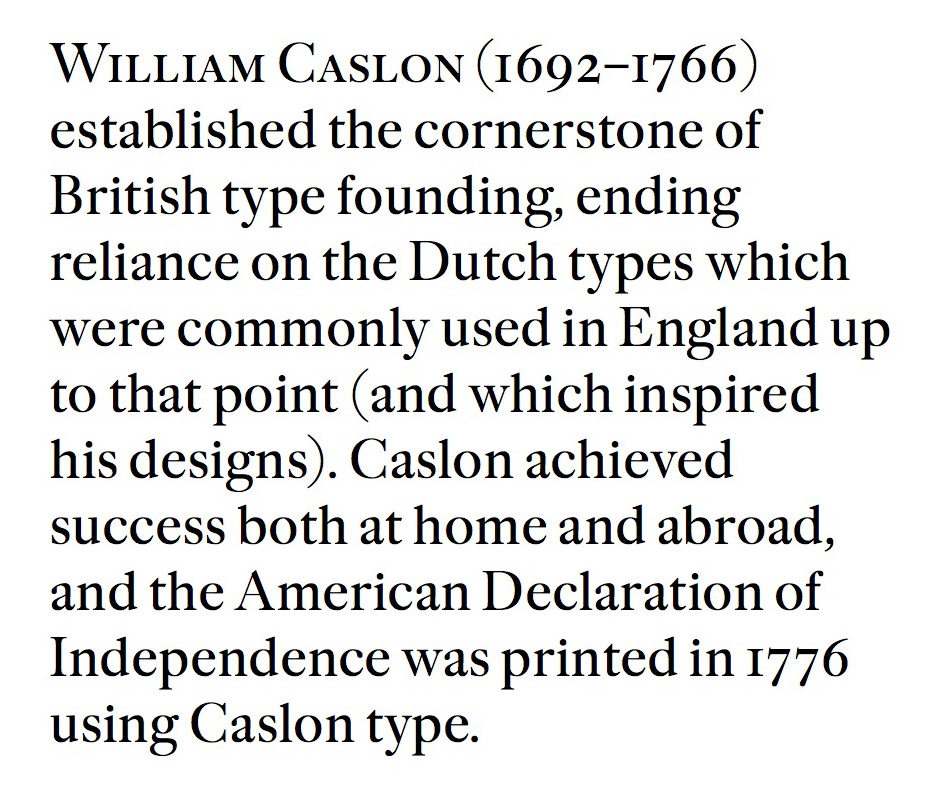
Пределы совершенства
Дав­но кру­тит­ся в го­ло­ве мысль за­пи­сать свои ощу­ще­ния от из­ме­не­ний фак­ту­ры, глад­ко­сти, иде­аль­но­сти кон­ту­ра в лет­те­рин­ге на кам­не, в кал­ли­гра­фии и шриф­те.
Эта мысль воз­ник­ла, ко­гда мы в Кем­бри­дже рас­смат­ри­ва­ли дос­ки, на­гра­ви­ро­ван­ные ма­стер­ской Кар­до­зо-Кин­дер­сли, иде­аль­ные с тех­ни­че­ской точ­ки зре­ния. По­ду­ма­лось, что ка­кие-то 20–30 лет на­зад они вы­гля­де­ли про­сто не­ве­ро­ят­но, не­уже­ли мож­но до­бить­ся та­ко­го со­вер­шен­ства, та­кой точ­но­сти ли­нии! А сей­час ма­ло кто осо­знаёт в пол­ной ме­ре, что это сде­ла­но вруч­ную (на­столь­ко гла­док и без­упре­чен ре­зуль­тат), и мы не мо­жем вос­хи­тить­ся ра­бо­той так, как вос­хи­ща­лись со­всем не­дав­но. До че­го не­ожи­дан­но, долж­но быть, для мно­гих по­вер­ну­лась ис­то­рия, и как из­ме­ни­лось вос­при­я­тие! Мог­ли бы пред­ска­зать са­ми ма­сте­ра, что вот так вдруг вме­сте с раз­ви­ти­ем тех­ни­ки глад­кость кон­ту­ра пе­ре­ста­нет вос­при­ни­мать­ся од­но­знач­но как иде­ал?
Па­мят­ная дос­ка фи­зи­ку Джо­се­фу Том­со­ну (1856–1940), об­на­ру­жив­ше­му элек­трон. Ма­стер­ская The Cardozo Kindersley Workshop, Кем­бридж. © Фо­то: Ве­ра Ев­стафье­ва, 2015
Глад­кость и бле­стя­щее со­вер­шен­ство кон­ту­ра руч­ной ра­бо­ты силь­но по­те­ря­ли свою цен­ность с по­яв­ле­ни­ем циф­ро­вых ин­стру­мен­тов (на­при­мер, в гра­ви­ро­ва­нии на кам­не). По­яви­лась воз­мож­ность (от­ча­сти ил­лю­зор­ная) для не­про­фес­си­о­на­ла до­би­вать­ся ре­зуль­та­та, ко­то­рый рань­ше тре­бо­вал боль­шо­го опы­та. В об­щем и це­лом за «ров­ность и глад­кость» те­перь от­ве­ча­ет ав­то­ма­ти­зи­ро­ван­ный ин­стру­мент. Че­ло­ве­че­ская ру­ка, на­о­бо­рот, ста­но­вит­ся но­си­те­лем не столь­ко ма­стер­ства и точ­но­сти, сколь­ко эмо­ци­о­наль­но­сти, спон­тан­но­сти — по край­ней ме­ре, в ожи­да­ни­ях зри­те­ля.
Си­сте­ма ко­ор­ди­нат пе­ре­вер­ну­лась. Те ве­щи, в ко­то­рых точ­ность руч­ной ра­бо­ты до­стиг­ла ка­ко­го-то сверхъ­есте­ствен­но­го ка­че­ства, вдруг ста­ли «про­ва­ли­вать­ся» в на­шем вос­при­я­тии и в на­шей оцен­ке. Ком­пью­тер де­ла­ет эту ра­бо­ту бы­стрее и де­ше­вле, при­смот­реть­ся мы не все­гда ус­пе­ва­ем, а при­кос­но­ве­ние ру­ки в иде­аль­ной руч­ной ра­бо­те по­чти не за­мет­но. На­учить ком­пью­тер де­лать так­ же, как это де­ла­ет жи­вой ма­стер, — ди­ко азарт­ная иг­ра... По­лу­ча­ет­ся, что со­вер­шен­ство­ва­ние но­во­го ин­стру­мен­та во мно­гом ин­те­рес­нее, чем ре­зуль­тат: вы­со­кое ка­че­ство уже до­стиг­ну­то, те­перь ин­те­рес­но де­лать то же са­мое, но дру­гим спо­со­бом (ско­рость и сто­и­мость остав­лю за рам­ка­ми).
Пре­дель­ной точ­но­сти в кал­ли­гра­фии до­би­вал­ся Гер­ман Цапф (1918–2015), ко­то­рый об­ла­дал уди­ви­тель­ным чув­ством иде­аль­ной фор­мы, не­ви­дан­ной рань­ше, и до­во­дил кал­ли­гра­фи­че­ские над­пи­си до со­вер­шен­ства, ре­ту­ши­руя кон­тур / Index Graphik
Глад­кость кон­ту­ра — как глад­кость до­ро­ги. По уха­бам не про­едешь, а по ров­ной и по­кры­той на­ле­дью до­ро­ге сколь­зишь и ле­тишь впе­ред. Сверх­глад­кий кон­тур бук­вы (да и дру­го­го объ­ек­та) за­даёт гла­зу вы­со­кую ско­рость (но не чте­ния, а ско­рее рас­смат­ри­ва­ния) — и взгляд не за­дер­жи­ва­ет­ся. Не­дав­но мы об­су­жда­ли с дру­зья­ми-кал­ли­гра­фа­ми, по­че­му ча­сто пре­крас­ней­шие кал­ли­гра­фи­че­ские ли­сты не чи­та­ют, хо­тя ав­тор при­да­ёт тек­сту боль­шое зна­че­ние. Воз­мож­но имен­но по той при­чи­не, что слиш­ком вир­ту­оз­ны и иде­аль­ны ли­нии, и взгляд про­бе­га­ет по ним без тру­да и очень бы­стро, на­сла­жда­ет­ся лёг­ко­стью дви­же­ния и ле­тит даль­ше.
Ра­бо­ты Рей­чел Ял­лоп — пре­дел иде­аль­но­сти кон­ту­ра, по ко­то­ро­му глаз сколь­зит и не мо­жет оста­но­вить­ся.
Рань­ше ше­ро­хо­ва­тость бу­ма­ги и рас­тис­ки­ва­ние крас­ки бы­ли не­из­беж­ны­ми, а те­перь в ка­ких-то слу­ча­ях мо­гут быть же­лан­ны­ми. Кон­струк­ти­вист­ские ри­сун­ки, чер­те­жи, шриф­ты на со­вре­мен­ной бу­ма­ге вы­гля­дят без­жиз­нен­но — в ори­ги­на­ле (мень­ше ве­ка на­зад!) они смяг­че­ны и оду­шев­ле­ны ося­за­емо­стью ма­те­ри­а­лов. Те же фор­мы, но в «иде­аль­ном» кон­ту­ре и без вы­ра­жен­ной фак­ту­ры бу­ма­ги те­ря­ют ком­му­ни­ка­тив­ность, взгляд про­ска­ки­ва­ет по ним.
Осо­бен­но сло­жен в «пе­ре­во­де» на со­вре­мен­ные ма­те­ри­а­лы «па­лоч­ный шрифт» — имен­но из-за то­го, что пре­дель­но прост и гео­мет­ри­чен. По­па­дая в мир, где гео­мет­рия ста­ла слиш­ком точ­ной (из­ви­ни­те за та­кой обо­рот), та­кой шрифт мо­жет стать не­ин­те­рес­ным и при­ми­тив­ным. В эпо­ху кон­струк­ти­виз­ма са­ма гео­мет­рия бы­ла ру­ко­твор­ной, ри­со­ван­ной, края гео­мет­ри­че­ских фи­гур ды­ша­ли ру­ко­твор­ной не­иде­аль­но­стью, по­это­му со­вре­мен­ные циф­ро­вые ин­тер­пре­та­ции кон­струк­ти­вист­ских шриф­тов из-за сво­ей чрез­мер­ной глад­ко­сти и точ­но­сти силь­но про­иг­ры­ва­ют тем ри­сун­кам букв, ко­то­рые пред­ло­жи­ли кон­струк­ти­ви­сты.
Мо­но­ши­рин­ный па­лоч­ный шрифт Б. Эм­ме из его кни­ги «Шрифт: Эле­мен­тар­ное ру­ко­вод­ство для прак­ти­че­ско­го ис­поль­зо­ва­ния в клу­бе, шко­ле, пи­о­нер-от­ря­де и т. д.» (Ле­нин­град, Гос. изд. изоб­ра­зи­тель­ных ис­кусств, 1931)
Ка­жет­ся, гля­нец и фак­тур­ность в гра­фи­че­ской куль­ту­ре в це­лом в каж­дый пе­ри­од со­хра­ня­ют при­мер­но оди­на­ко­вые про­пор­ции, про­сто пе­ре­ме­ща­ясь из од­ной сфе­ры в дру­гую, ме­ня­ясь ме­ста­ми — от кал­ли­гра­фии к на­бор­но­му шриф­ту, в ри­со­ван­ные над­пи­си и обрат­но. Если точ­ность и гля­нец вос­тор­же­ство­ва­ли в шриф­то­вом ди­зай­не — в кал­ли­гра­фии уси­лит­ся фак­тур­ность, и на­о­бо­рот, ко­гда кал­ли­гра­фия бы­ла точ­нее пе­чат­но­го кон­ту­ра, шрифт бо­рол­ся, но не про­би­вал­ся к точ­но­сти вос­про­из­ве­де­ния. Толь­ко пу­ан­со­нист, воз­мож­но, гре­зил иде­аль­ным кон­ту­ром, ко­то­рый на ли­сте ста­нет та­ким же иде­аль­ным, как и в пу­ан­со­не, ко­то­рый он вы­ре­за­ет.
Ка­кой про­стор для дис­кус­сий и вы­бо­ра даёт эта раз­ни­ца меж­ду ре­нес­санс­ным пу­ан­со­ном и от­тис­ком для ди­зай­не­ров, ко­то­рые вос­ста­нав­ли­ва­ют клас­си­че­ские шриф­ты: брать за об­ра­зец пу­ан­со­ны, или от­тиск, или что-то сред­нее? Ка­кая фор­ма бук­вы бы­ла же­лан­ной, ка­ким бы­ло на­ме­ре­ние пу­ан­со­ни­ста? Ка­кую по­прав­ку на не­ров­ность пе­ча­ти, гу­сто­ту крас­ки, ре­льеф­ность бу­ма­ги он за­кла­ды­вал в ди­зайн шриф­та? И что бы­ло слу­чай­но­стью или не­из­беж­но­стью?
Раз­во­рот из кни­ги Джейм­са Сат­то­на (James Sutton) и Ала­на Бар­тра­ма (Alan Bartram) An Atlas of Typeforms.
© Фо­то: Ве­ра Ев­стафье­ва / Percy Lund, Humphries & Co Ltd., London, 1968.
По­до­зре­ваю, что сим­во­лом точ­но­сти во­все не все­гда был на­бор­ный шрифт, так тес­но свя­зан­ный се­го­дня для нас с ме­ха­ни­зи­ро­ван­ным, ма­шин­ным ми­ром. Бы­ло и вре­мя, ко­гда, на­при­мер, не бы­ло ни­че­го точ­нее и тонь­ше офор­та, а кал­ли­гра­фия остро­ко­неч­ным пе­ром пре­вос­хо­ди­ла сво­ей без­упреч­но­стью все дру­гие тех­ни­ки со­зда­ния букв. Это уди­ви­тель­но, и мож­но пред­по­ла­гать, что про­цесс, ко­то­рый на ко­рот­ком рас­сто­я­нии вы­гля­дит как со­вер­шен­ство­ва­ние од­ной тех­ни­ки и до­ве­де­ние её до мак­си­маль­но­го ка­че­ства, при рас­смот­ре­нии из­да­ли ока­зы­ва­ет­ся все­го лишь од­ним из эпи­зо­дов не­пре­кра­ща­ю­ще­го­ся ко­ле­ба­ния и пе­ре­те­ка­ния свойств. До­стиг­нув край­ней фак­тур­но­сти, тех­ни­ка не ис­чер­па­ет се­бя, не вы­ро­дит­ся, а от­пря­нет и на­пра­вит­ся ис­кать дру­гие вы­ра­зи­тель­ные сред­ства, воз­мож­но, в точ­но­сти и лос­ке.
Мне ка­жет­ся, что в ка­те­го­рию «фак­ту­ры как приёма» не­ров­ность кон­ту­ра пе­ре­шла толь­ко в се­ре­ди­не ХХ ве­ка. И очень ве­ро­ят­но, что это на­ча­лось имен­но в то вре­мя, ко­гда ти­по­гра­фи­ка бы­ла на пи­ке «ме­ха­ни­зи­ро­ван­ной» эсте­ти­ки (мо­дер­низ­ма). Ма­сте­ра ве­ка­ми бо­ро­лись за точ­ность вос­про­из­ве­де­ния шриф­та, и се­го­дня у нас и век­тор то­чен, и бу­ма­га пре­крас­на, и крас­ка мел­ко­дис­перс­ная — всё хо­ро­шо! Од­на­ко нам вновь за­хо­те­лось не­со­вер­шен­ства, и фак­ту­ра, не­ров­ность — те­перь ис­клю­чи­тель­но ху­до­же­ствен­ный приём, а не не­пре­одо­ли­мый фак­тор.
На­ме­рен­ная и управ­ля­е­мая ше­ро­хо­ва­тость как приём. Со­ло­мон Те­лин­га­тер. Но­во­год­нее по­здрав­ле­ние, 1960-е. Ори­ги­нал / Рос­сий­ская го­су­дар­ствен­ная биб­лио­те­ка.
При од­ном и том же «те­ле» фор­мы кон­тур мо­жет быть как глад­ким, так и «по­трёпан­ным», что ме­ня­ет и до­пол­ня­ет об­раз. Рва­ный край над­пи­си даёт гла­зу воз­мож­ность доль­ше бро­дить по ней и рас­смат­ри­вать, рас­по­ла­га­ет к бо­лее близ­ко­му кон­так­ту. Ин­те­рес­но, шрифт и кал­ли­гра­фия — па­ра ли это, ме­ня­ю­ща­я­ся ме­ста­ми в сво­ей экс­прес­сии и, на­о­бо­рот, в иде­аль­ной точ­но­сти? Два про­ти­во­по­лож­ных свой­ства кон­ту­ра, оди­на­ко­во не­об­хо­ди­мые для гла­за, при из­ме­не­нии од­ной тех­ни­ки стре­мят­ся про­явить­ся в дру­гой тех­ни­ке и сфе­ре.
Юрий Гор­дон. Га­зе­та Alcools. Вы­пуск № 7, 2006. Для оформ­ле­ния «Ал­ко­го­лей» ди­зай­нер раз­ра­бо­тал шриф­то­вую се­мью Ко­стро — ан­ти­кву и гро­теск. Обе гар­ни­ту­ры бы­ли на­ри­со­ва­ны в «Пей­н­те­ре» са­мой при­ми­тив­ной ки­стью, «как если бы на­ре­за­ны вруч­ную для вы­со­кой пе­ча­ти без спе­ци­аль­ных ин­стру­мен­тов» (по сло­вам ав­то­ра), а по­сле пе­ре­не­се­ны в «Фонтлаб». © Юрий Гор­дон / Лич­ный ар­хив.
В 1990-е го­ды — с их гранж-шриф­та­ми, «му­сор­ны­ми» шриф­та­ми — по­сле при­кос­но­ве­ния к пре­де­лу иде­аль­но­сти фор­мы слу­чил­ся от­кат от это­го ру­бе­жа, ри­ко­шет в сто­ро­ну фак­тур­но­сти. Би­льярд­ный шар ка­тит­ся в обрат­ном на­прав­ле­нии. Лю­бо­пыт­но, что в XIX ве­ке (во вре­ме­на пер­во­го рас­цве­та ак­ци­дент­ных шриф­тов), ко­гда тех­но­ло­гии не да­ва­ли иде­аль­но­го края в пе­ча­ти, не воз­ни­ка­ло и же­ла­ния сде­лать кон­тур рва­ным.
Как толь­ко про­изо­шло очи­ще­ние шриф­то­во­го кон­ту­ра от по­мех пе­ча­ти и был до­стиг­нут ми­ни­ма­лизм в кон­ту­ре, этих по­греш­но­стей ста­ло тут же не хва­тать, их осо­знан­но со­зда­ва­ли и до­бав­ля­ли в тех слу­ча­ях, где это бы­ло умест­но. Лоск со­вре­мен­ной тек­сто­вой по­ло­сы, на­вер­ное, при­вёл бы в тре­пет и ужас тех со­вре­мен­ни­ков Бас­кер­ви­ля, ко­то­рые ру­га­ли его слиш­ком чёт­кую пе­чать, опа­са­ясь за зре­ние чи­та­те­лей. Пред­ставь­те, как они смот­рят на стра­ни­цу ка­ко­го-ни­будь глян­це­во­го жур­на­ла и ви­дят на снеж­но-бе­лой ме­ло­ван­ной бу­ма­ге пре­дель­но чёт­кие и ров­ные ря­ды букв — на их взгляд, ни­че­го жи­во­го. Со­гла­си­тесь, вид тек­сто­вой по­ло­сы бук­валь­но за два-три сто­ле­тия из­ме­нил­ся очень силь­но. Вос­ста­нав­ли­вая шриф­ты 300-лет­ней дав­но­сти в циф­ро­вом ви­де, мы не­воль­но лу­ка­вим, если пре­под­но­сим этот шрифт как «тот са­мый», «до­сто­вер­ный». Из­ме­ни­лись тех­но­ло­гии пе­ча­ти и из­го­тов­ле­ния всех ти­по­граф­ских ма­те­ри­а­лов, и на­бор уже ни­ко­гда не бу­дет вы­гля­деть «как то­гда». Мы в лю­бом слу­чае со­зда­ём но­вый шрифт, об­раз, но­вую фак­ту­ру на стра­ни­це.
Ведь мы не мо­жем уви­деть шрифт и текст, им на­бран­ный, от­дель­но от бу­ма­ги, от её цве­та и фак­ту­ры, про­зрач­но­сти и плот­но­сти или же от­дель­но от све­че­ния экра­на, его яр­ко­сти и раз­ре­ше­ния? Ко­неч­но, в про­цес­се со­зда­ния шриф­та ди­зай­нер ра­бо­та­ет над фор­мой как бы в ва­ку­у­ме, но диа­па­зон все­воз­мож­ных по­верх­но­стей, на ко­то­рые шрифт ля­жет се­го­дня и в бли­жай­шем бу­ду­щем, до­ста­точ­но кон­кре­тен, име­ет свои гра­ни­цы и от­ли­ча­ет­ся от диа­па­зо­на 300-лет­ней дав­но­сти.
Те­перь, ра­бо­тая над шриф­том для чте­ния с экра­на, ку­са­ешь лок­ти и при­знаёшь­ся се­бе, что уже не придёт­ся при­ни­мать ни­ка­ких ре­ше­ний, про­дик­то­ван­ных огра­ни­че­ни­я­ми тех­но­ло­гии, — а как бы­ло при­ят­но со­всем не­дав­но, бук­валь­но лет 10–20 на­зад, на­хо­дить ре­ше­ния на­сто­я­щей про­бле­мы! На­при­мер, низ­кое раз­ре­ше­ние не поз­во­ля­ет со­зда­вать глад­кий и слож­ный ри­су­нок и нуж­но ис­кать но­вые ре­ше­ния. Ка­кой по­да­рок! Сей­час эти огра­ни­че­ния ми­ни­маль­ны, экра­ны пре­крас­но отоб­ра­жа­ют де­та­ли шриф­та, и по­иск в про­цес­се ра­бо­ты идёт ско­рее в плос­ко­сти сти­ля, ат­мо­сфе­ры, ай­ден­ти­ки, пла­сти­ки...
Шрифт Literata для чте­ния на экра­не, со­здан­ный для при­ло­же­ния Google Play Books ком­па­ни­ей TypeTogether в 2014 го­ду. Раз­ра­бот­ка ки­рил­ли­цы — Ве­ра Ев­стафье­ва. При­мер тек­сто­во­го шриф­та с уз­на­ва­е­мым ха­рак­те­ром, близ­кий к тем, ко­то­рые мы при­вык­ли ви­деть в кни­гах с дет­ства, ко­гда ещё не по­яви­лись элек­трон­ные кни­ги. © TypeTogether
Кон­тур бук­вы пой­ман, он аде­ква­тен за­мыс­лу ди­зай­не­ра, борь­ба с тех­но­ло­ги­ей за­кон­чи­лась. Те­перь мож­но про­дол­жать бо­роть­ся за со­вер­шен­ство дру­гих па­ра­мет­ров — сти­ля, об­ра­за, аутен­тич­но­сти и мно­гих дру­гих, но со­вер­шен­ство кон­ту­ра и точ­ность вос­про­из­ве­де­ния уже до­стиг­ну­ты. Нам боль­ше не нуж­но бо­роть­ся за хо­ро­шую раз­ли­чи­мость букв в пе­ча­ти (как бы­ло во вре­мя про­ек­ти­ро­ва­ния шриф­та Bell Centennial) или хо­ро­шее вос­про­из­ве­де­ние букв на экра­нах с низ­ким раз­ре­ше­ни­ем (вспо­мним про­ек­ты шриф­тов Georgia, Verdana, Cleartype) — в це­лом эти про­бле­мы уже ре­ше­ны.
Увы и ах для на­ше­го по­ко­ле­ния, ведь мы то­же бы­ли бы ра­ды ре­шать как эсте­ти­че­ские, так и тех­но­ло­ги­че­ские про­бле­мы. Но се­го­дняш­ние тех­но­ло­гии поз­во­ля­ют де­лать по­чти всё что угод­но и вы­би­рать в каж­дом кон­крет­ном слу­чае не­об­хо­ди­мый ха­рак­тер кон­ту­ра — иде­аль­но-от­решён­ный или ося­за­емый. Ка­кие за­да­чи те­перь ре­шать? По­смот­рим!